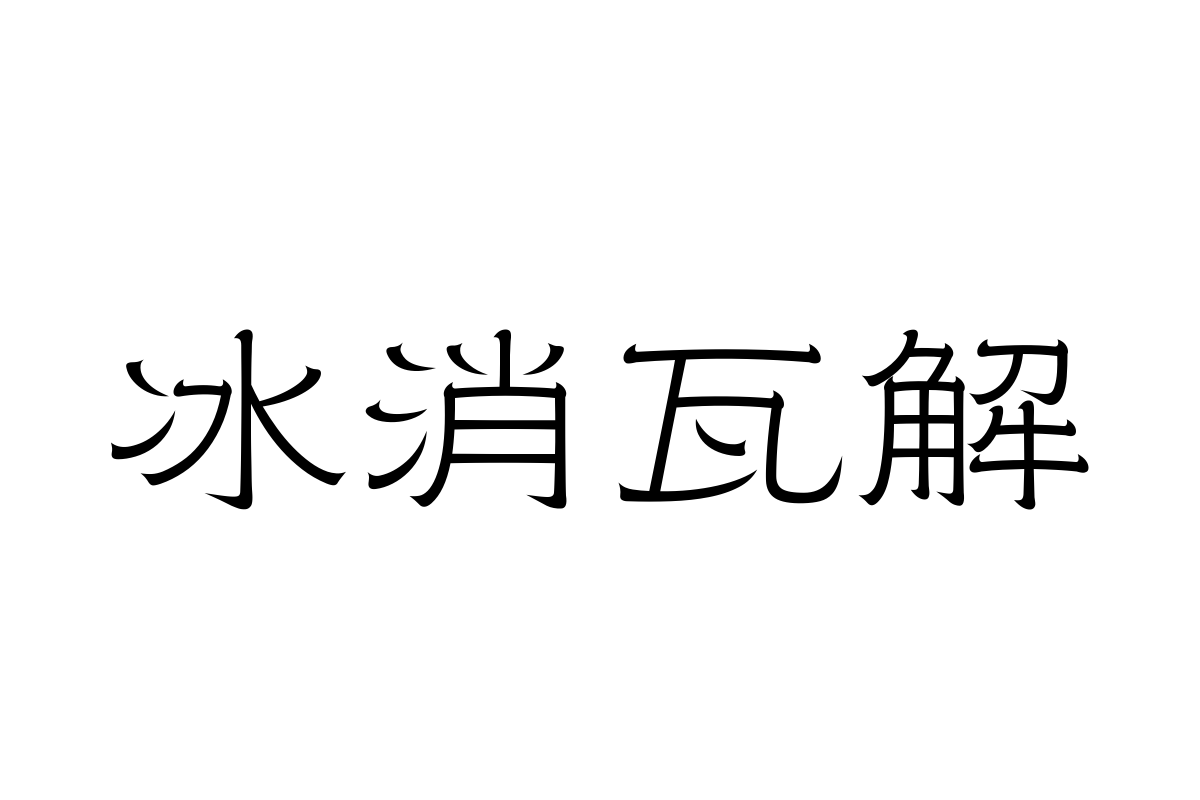
汉仪赤云隶 45W是一款具有独特风格的中文字体。这款字体的设计灵感来源于古代书法艺术,线条流畅、笔触有力,给人一种古朴而庄重的感觉。它适用于各种需要强调文字美感和文化底蕴的场合,如广告设计、品牌标识、书籍封面等。
汉仪赤云隶 45W字体的特点如下:
1. 笔画粗细适中,既有力度又不失柔美,适合用于标题和重点文字。
2. 字形结构严谨,线条起伏有致,给人以强烈的视觉冲击力。
3. 字体风格古朴,具有较强的传统韵味,适合传统文化主题的宣传和展示。
4. 支持多种字重和行距设置,满足不同应用场景的需求。
总之,汉仪赤云隶 45W字体是一款具有独特魅力的中文字体,适合用于各类需要强调文字美感和文化底蕴的设计项目。